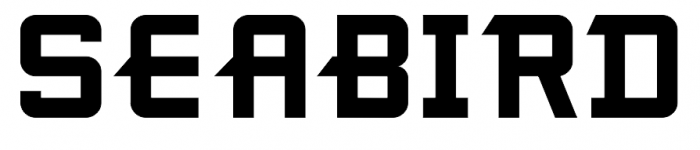
kann mir jemand sagen, welche Schriftart das hier ist. Habe schon verschiedene Schrifterkennungsanbieter ausprobiert, aber leider keinen Treffer gehabt. Ist auf nem Kanu aufgedruckt.
Hast Du auch versucht, die horizontalen Streifen zu entfernen? Die könnten nachträglich hinzugefügt worden sein.
riMkam sie jedenfalls recht bekannt vor, und meinte, sie unter Ray Larabie‘s Fonts verorten zu können - fand das aber nicht.
diese Querstreifen entstammen sicherlich dem Gradient-Effekt vom (wahrscheinlich) Fontlab, wird recht oft verwendet, um mit nur einem Klick einen weiteren Font bauen zu können.
Generell aber können die Font-Suchprogramme mit verzerrten Bildern, die noch Teile anderer Elemente enthalten nichts anfangen, auch die Kontraste müssen recht hoch und gleichmäßig sein. hier das Bild umgekehrt und entzerrt:
da dies bei den Suchprogrammen ins leere führte hab ich dir den Text mal ohne diesen Gradient-Effekt nachskizziert:
aber auch da passen die Schrifterkenner, vielleicht bringt es aber auf die Fährte...